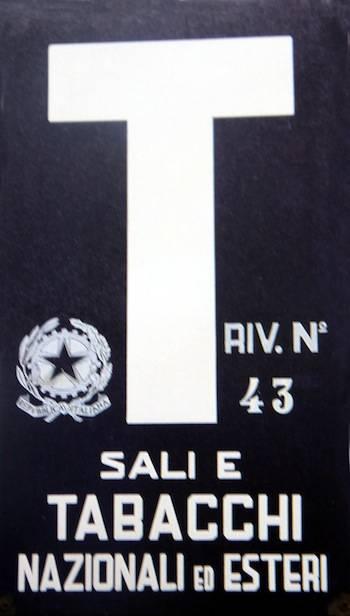
Suche Schriftart "Sali e Tabacchi" der typischen 60er-Jahre-Schilder
Hallo! Ich bin auf der Suche nach der Schriftart, mit der "Sali e Tabacchi" auf den typischen italienischen Emailleschildern geschrieben ist, die draußen an den Tabakgeschäften hingen. Würde mich freuen, wenn jemand eine Idee - auch wenn nur ähnlich - hat. Liebe Grüße
Ich bin mal so frei und belebe dieses Thema wieder.
Auch ich wäre daran interessiert, den Font zu kennen.
Auch dort gab es keine Antwort.
Oder empfiehlst du, das dortige Thema wiederzubeleben?
Die Antwort, die der Artikel gibt, ist, dass es keine Antwort auf die Frage nach der Schrift geben kann, da die Beschriftung mit hoher Wahrscheinlichkeit handgezeichnet und damit werkstattspezifisch ist, sofern irgendjemand überhaupt eine Vorlage erstellt hat und nicht jedes Schild individuell erstellt.
Wobei es in Italien soviele dieser Läden und damit dieser Schilder gibt, dass es eigentlich kaum vorstellbar ist, dass diese nicht irgendwo in Serie hergestellt wurde. So genau hab ich mir diese Schilder auch nie angesehen, aber zumindest ähnlich sind sich die Schriften darin schon. Egal in welcher Stadt - zumindest nördlich von Rom. Wäre also zumindest möglich, dass die ausstellende Behörde (ursprünglich waren diese Läden als quasi Altersversorgung ehemaliger Soldaten und Staatsangestellter gedacht und wurden deshalb streng lizensiert) schon nach Art auch italienischer Bürokratie eine Vorschrift auch zum Schrifttyp erlassen haben könnte. Natürlich nicht einen Computerfont, aber vielleicht irgendeine Schriftschablone bzw. Schablonenschrift.  Diese Schilder waren bzw. sind ja quasi ein amtliches Zertifikat.
Es sind ja mindestens zwei Schriften in Gebrauch, eine sehr konstruierte Sans  und eine Serifenschrift (Zahlen). Und meines Wissens obliegt die Kennzeichnung des Ladens dem Betreiber, der damit wirbt, dass er zertifiziert ist. Das sind keine amtlich bestellten Schilder (im Sinne eines Straßen- oder Hinweisschildes).
Es gibt diese Schilder in der Tat je nach Herstellungstechnik mit unterschiedlichen Schriften.
Mag sein, dass Italien da keine Norm angelegt hat.
Die emailierten Schilder aus den 60er/70er Jahren haben diese “hängende Gürtellinie”.
Emailschilder werden idR in einem schablonierten Glasgranulatverfahren hergestellt.
Vielleicht war das im Emailierwerk tatsächlich dem Schablonenschneider freigestellt.
Da wäre ich mir nicht so sicher. Das Staatswappen mit drauf, die Laden(Lizenz)Nummer, relativ einheitliche Farbgebung und das meiner Erinnerung nach immer gleiche T ... und so schön sind die Schilder ja auch nicht, dass sie "Werbung" wären. Aus dem Salz- und Tabakmonopol ist nun zwar nur der Tabak geblieben ist, die Nahverkehrstickets sind aber dazugekommen und somit kann das durchaus eine "amtliche" Sache sein ... auf italienisch halt mit einer gewissen herstelltechnischen Bandbreite möglicherweise. Ich hab allerdings nirgendwo (zumindest bewußt) ein typografisch oder gar farblich deutlich anderes Schild gleichen Inhalts gesehen ... das könnte Gründe haben. Gerade in Italien hätte es bei freier Auswahl doch sicher ganz schnell deutlich "stylischere" oder zumindest auffallendere Schilder gegeben. Man müßte halt mal einen echten Tabacchaio fragen ...
Das S in »SALI E« und in »ESTERI«, das R in »RIV. №« und in »ESTERI«, das E in »SALI E« und in »ESTERI«, das A in »SALI E« und in »NAZIONALI« stimmen nicht überein; die Ziffern passen nicht zur sonstigen Schrift: Das alles spricht für mich eindeutig gegen eine Druckschrift. Das spricht aber nicht dagegen, dass es eine einheitliche Vorlage für die Schilder gibt.
Wenn eine Schrift, die in die Richtung geht, ausreicht, wie wäre es hiermit:
Das S stimmt nicht, der Querstrich beim A ist zu hoch, die Strichenden bei L, E und Z sind angeschrägt, beim B sind die Größenverhältnisse von Kopf und Bauch umgekehrt und das R hat kein gerades Bein. Aber ich konnte leider auf die Schnelle nichts ähnlicheres finden.
Auch hässliches Design überlebt, wenn es einfach nur ausreichend gewohnt ist.
Wobei dieses Design offenbar erst irgendwann Ende der 50er / Anfang der 60er eingeführt worden ist, denn diese Schilder waren bis in die 50er Jahre hinein ganz anders (u.a. oval). Erst ab den 60ern gibt sie (anscheinend nur in Blau und Schwarz) in diesem "Design", welches aber im Wesentlichen (zumindest für grafischen Laien - Durchschnittsbürger) gleich geblieben ist. Das lässt doch irgendeine nationale Vorschrift oder Vorgabe vermuten ... gerade in Italien. Wobei die schwarzen, die ich bisher im Web gefunden habe, anscheinend alle aus Südtirol stammen - also einer Region mit besonderem Status. Ist natürlich nur eine Vermutung und die Auswahl der Bilder ist ja auch eher zufällig. Andererseits erstaunt angesichts der weiten Verbreitung dieser Schilder, dass sie nicht gerade zahlreich, dafür aber recht teuer gehandelt werden.